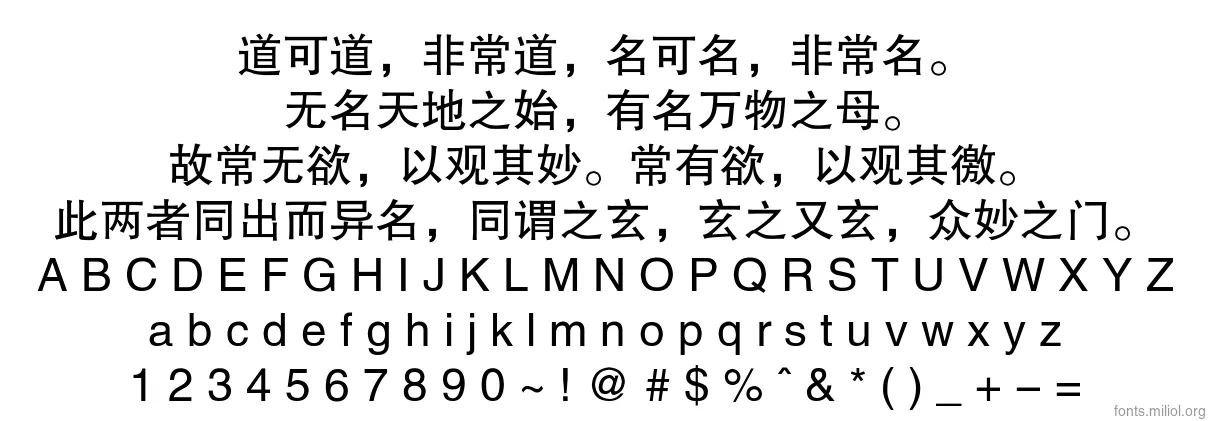
**方正黑体简体 (FZHei-B01S) (FZHTJW--GB1-0) 字体简介**
方正黑体简体(FZHei-B01S)是一款由方正字库设计的中文字体,属于现代黑体系列,以其简洁、稳重的风格广泛应用于印刷、广告和数字媒体领域。该字体笔画均匀,结构严谨,兼具传统黑体的庄重感和现代设计的流畅性,适合标题、正文等多种排版需求。FZHTJW--GB1-0是其特定版本编号,符合国家标准字符集(GB2312-80),确保对常用汉字的完整支持。
方正黑体简体的清晰度和可读性使其成为商业设计、品牌宣传的优选字体之一。无论是海报、书籍还是网页设计,它都能传递专业、大气的视觉感受。用户需通过正规渠道获取授权,以确保合法使用。